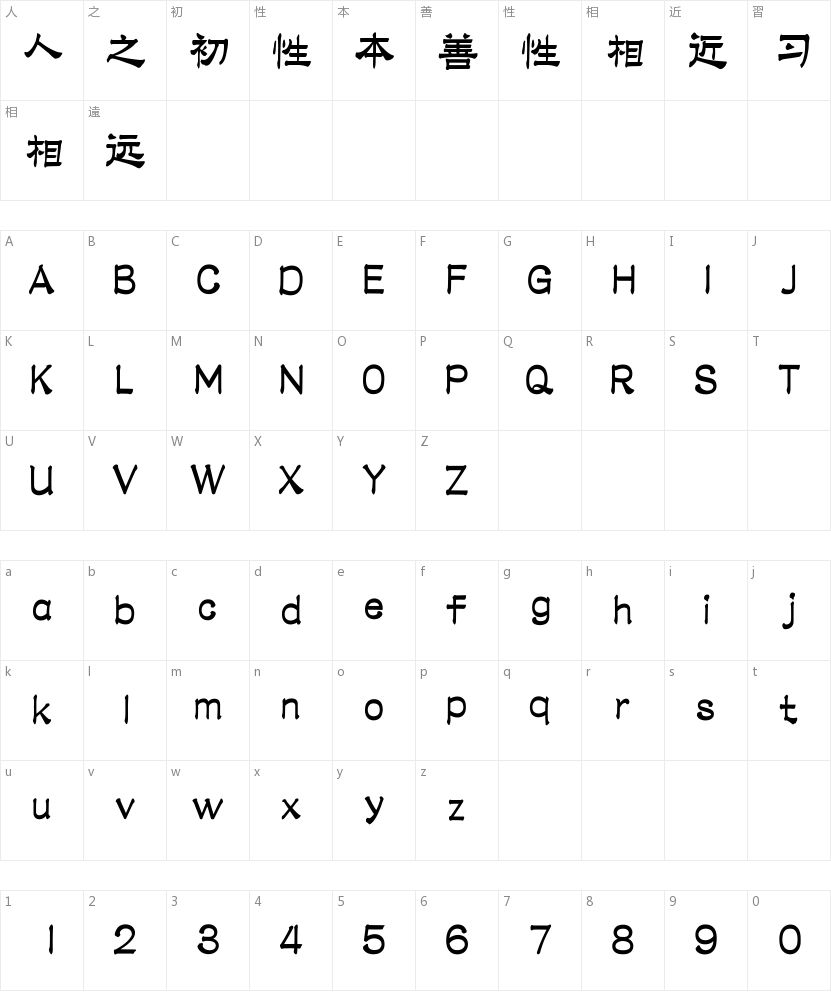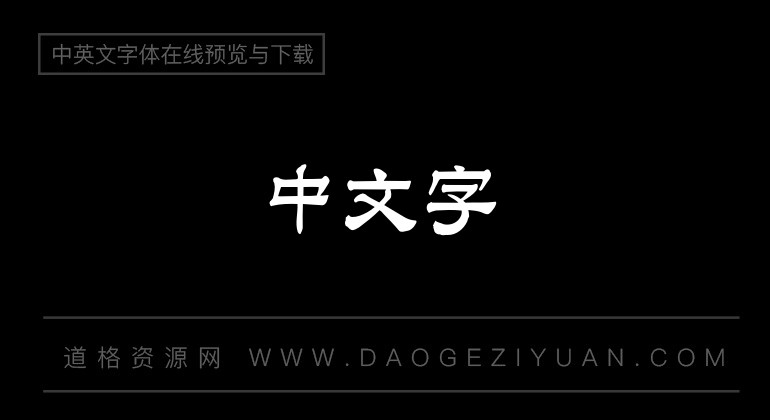
蒙纳简隶书
蒙纳简隶书(Monotype Modern)是一种拥有现代外观的简体字体,由蒙纳米特(Monotype)公司设计。它具有精细的细节,而且拥有良好的可读性和可视性,可以用于各种类型的文字,包括印刷品、报纸、杂志、书籍、广告等。它的字体框架由细线和粗线组成,两者之间有一定的差别,细线更加精细,而粗线则更加显眼,可以用于更多的文字类型。
蒙纳简隶书是一款非常不错的手写艺术字体,具有很好的视觉感,适合于文化类的宣传设计、商业类品牌的广告和产品包装设计以及个性化文字排版等较多场景。
蒙纳简隶书字符映射图